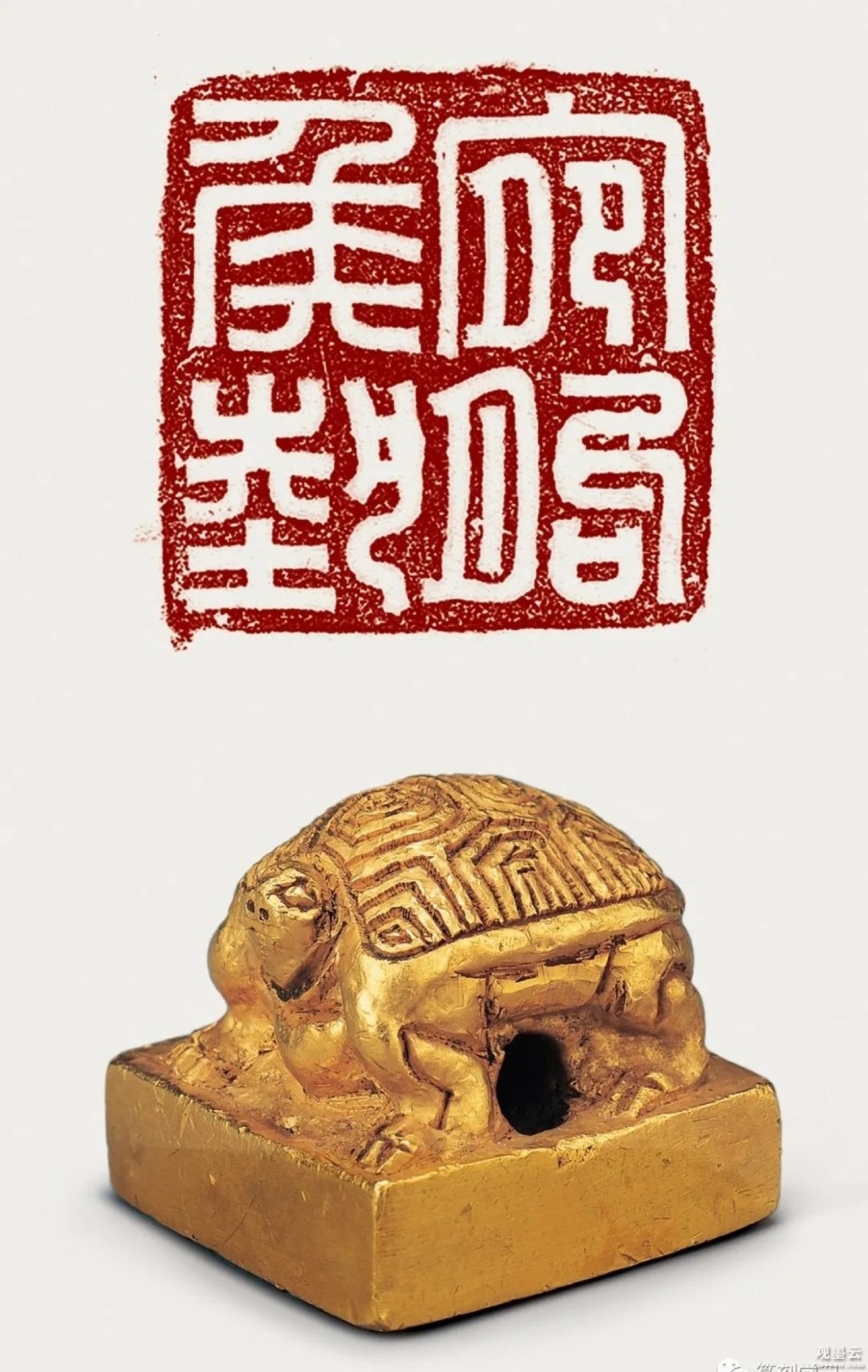
△“宛朐侯埶”金印
历史年代:【西汉】
尺寸:通高2.1、钮高1.45、边长2.3厘米
来源:徐州簸箕山汉墓
介绍:
金印出土于死者腰部略偏上。印为龟钮,先铸造成型后,经雕刻加工而成。龟首较小、稍外伸上昂,背部拱起,背上刻饰有由外向内相套含的六边形、五边形、四边形以象征龟甲,四是挺立,爪形分明。印台为方形,四边略有外弧。龟钮与印台间有一圆形横穿孔,印文为白文篆体“宛朐侯埶”四字,笔势匀称,结体端正。印重127克。
据史书记载,刘埶为楚元王第六子,高祖刘邦之侄,楚王刘戊的叔父。景帝时刘埶被封为宛朐侯。宛朐为古县名,也称宛句,故城在今山东菏泽西南,景帝时属济阴郡。公元前154年刘埶参与吴楚七国之乱,被平叛后,宛朐国除。
汉代对玺印的铸制有着严格的规定,以印钮的不同形制来显示职位官阶。据《汉官仪》记载:皇帝玉玺螭虎钮、皇后金玺螭虎钮;诸侯王用黄金橐驼钮;列侯、丞相、太尉、大将军用黄金龟钮等。宛朐侯属列侯位,所以使用黄金龟钮印。汉印一般分官印和私印两种,官印主要是刻官职,私印则是刻名字。而这枚金印上刻“宛朐侯埶”四字,同时含官职和名,从目前出土的汉代玺印看,这种官职和名字同刻于一印,是比较少见的。此印应该是属于私印的一种,可能是为了陪葬而专门制的。